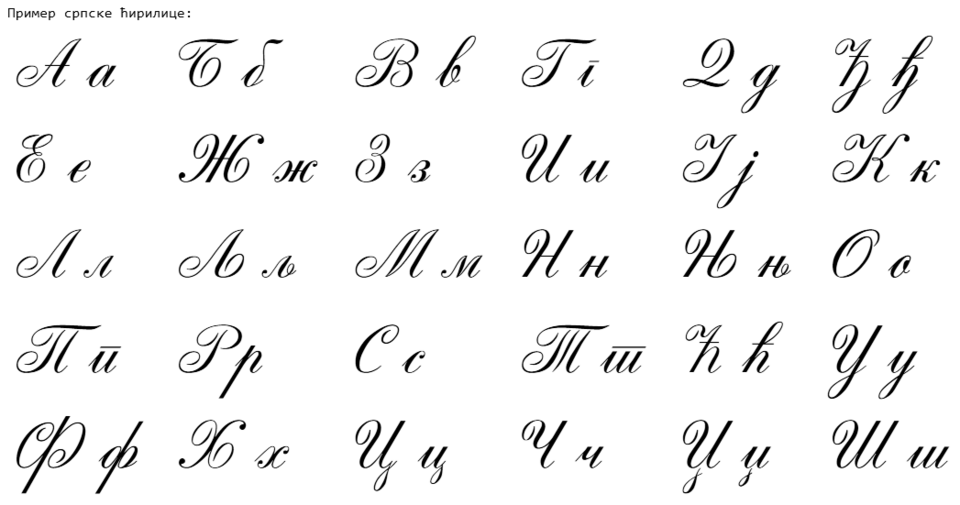
30+ Бесплатных рукописных шрифтов | by Writes
С новыми трендами на типографику дизайнеры все больше и больше нуждаются в уникальных шрифтовых сочетаниях.
Шрифтов не бывает много, тем более рукописных. Именно поэтому мы сделали подборку крутых, рукописных шрифтов. Все шрифты бесплатны и готовы к использованию.
Кириллица там тоже есть!
Кириллические рукописные шрифты в дизайне сайта
Нравятся рукописные шрифты, но считаете что они не впишутся в дизайн вашего сайта? Несмотря на все свои витиеватости и завитушки, рукописные шрифты могут отлично смотреться в заглавии, в тексте или в дизайне логотипа. Они отлично сочетаются с другими шрифтами и притягивают к себе внимание даже если выступают в роли второго, дополнительного шрифта.
А для того, чтобы вы в этом удостоверились, мы сделали подборку дизайнов, в которых кириллические рукописные шрифты очень органично смотрятся в дизайне.
Рукописные шрифты в дизайне
Посмотрите, как можно использовать рукописные шрифты в оформлении страниц сайтов или логотипах.
Меню на сайте кондитерской
Надпись на Главной странице и буквенный логотип сайта пекарни
Буквенный логотип магазина органической еды
Второй шрифт в дизайне сайта ресторана
Рукописный шрифт в дизайне гастрономического интернет-магазина
Заглавный шрифт в Keynote презентации
Бесплатные кириллические рукописные шрифты
Вдохновившись идеями для использования рукописных шрифтов, предлагаем вам выбрать один из предложенных ниже и смело использовать в своём проекте.
Рукописный шрифт обязательно добавит уникальности вашему сайту и понравится пользователям. Он сразу привлечет внимание среди шрифтов семейства Sans Serif.
Кириллический шрифт Brush Flair Cyr
Кириллический шрифт Intro Script R h3 Base
Кириллический шрифт LainyDay
Кириллический шрифт Angelface [Rus by me]
Кириллический шрифт Poetica Chancery
Кириллический шрифт BetterTogether-Script
Вы ищете отличный бесплатный рукописный шрифт для вашего проекта? Тогда вы пришли в нужное место. Лучшие рукописные шрифты бывают разных исполнений и с различными стилями. Они могут быть тонкими, смелыми и блочными, чистыми и простыми. Они находятся в той же области, что и курсивные шрифты, но с меньшим количеством ограничений.
В этом списке мы собрали несколько лучших бесплатных рукописных шрифтов, которые вы можете использовать.
Brown Bag Lunch
Brown Bag Lunch вдохновлен мамой автора Кевина Ричи. Раньше она писала его имя на его ланч-сумке, а созданный им шрифт напоминал наспех записку. Текстура похожа на маркер, а наклонное качество ощущается как индивидуальный подход.
Shopping Script
Если вам нужен плавный рукописный шрифт с собственным фирменным стилем (без каламбура), то в этом может помочь Shopping Script. Этот набор рукописных шрифтов, созданный венгерским дизайнером Роландом Хюсе, охватывает ваши основные символы и цифры (A-Z, 0-9, прописные и строчные буквы).
Timothy
Добавьте подлинный рукописный вид к своим дизайнам с этим великолепным рукописным шрифтом Something Wild. Something Wild, доступный на Pixelbuddha, придаст вашему дизайну индивидуальность, сделав его идеальным для дизайна постеров и флаеров.
Stay Classy
Этот хорошо названный рукописный шрифт — один из самых классных.